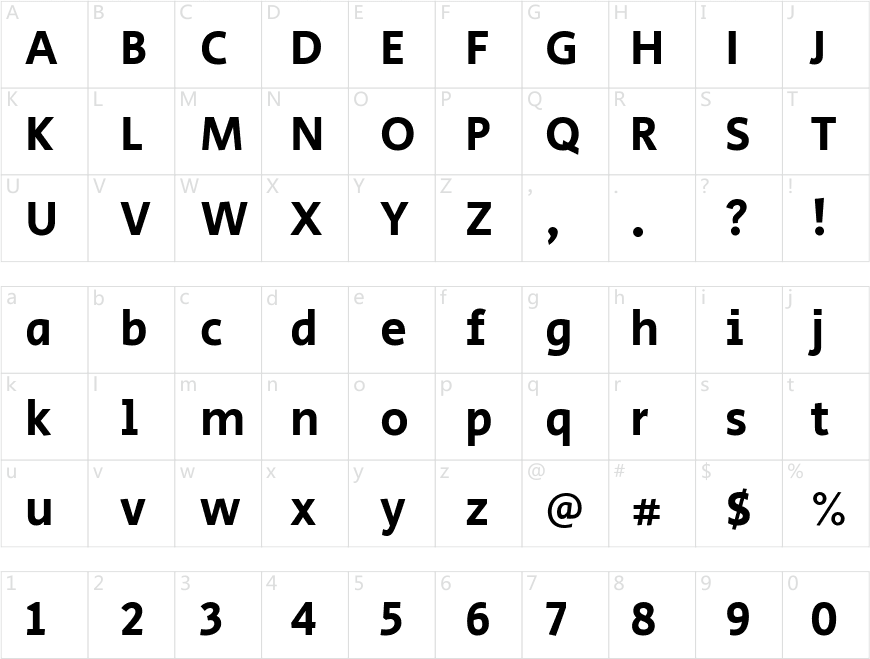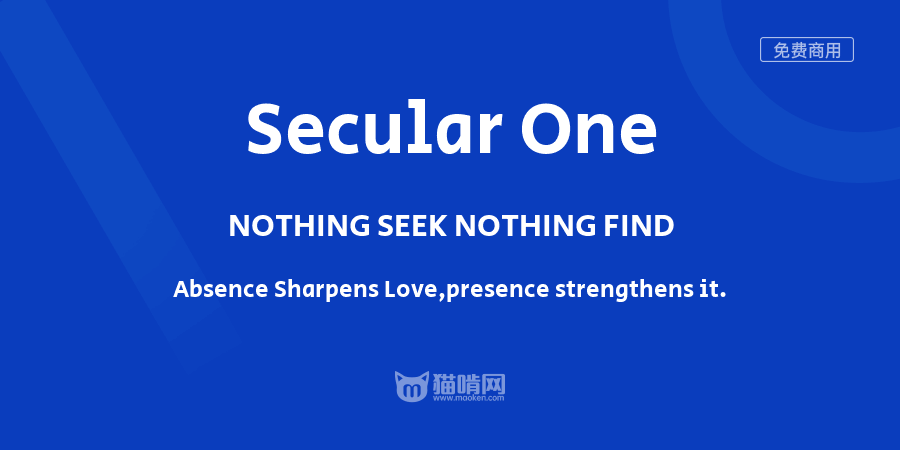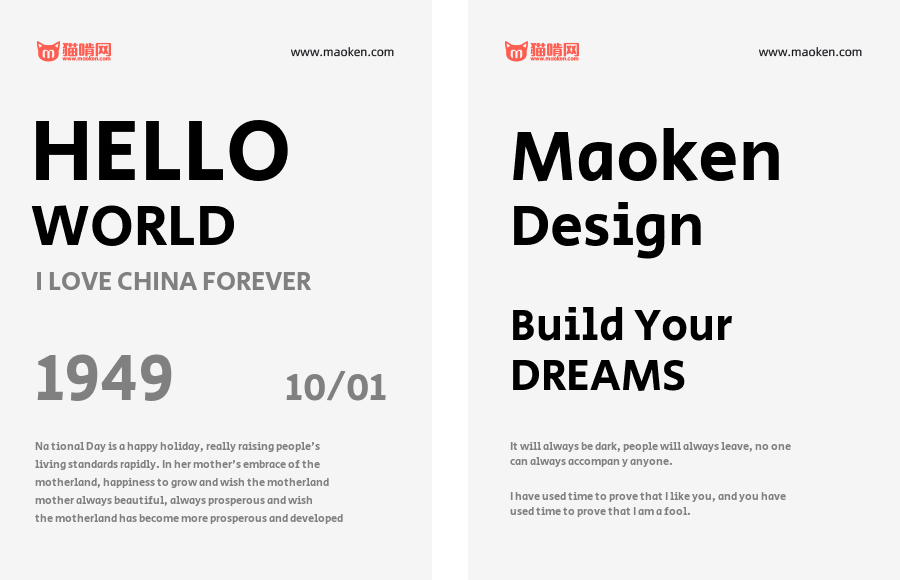
Secular One
Secular One是一款源自希伯来文和拉丁文的人文无衬线体(黑体),具有单一粗细。在发布时(2016年),市面上希伯来文无衬线体(黑体)文本字体还不多见。设计师Michal Sahar希望打造一款清新、“随和”的字体,既简单而不缺乏特色,友好而不过于恭维或设计过度,笔直而不夸张……并且在字体较小或段落较长时依然保持高度可读性。当字体尺寸较大时,Secular的字形表现依然出色,展现出精致且独特的元素,使其既适合品牌设计,也适合排版长篇文本。
2023年6月的更新增加了更大的字形集,并修复了一些小问题。